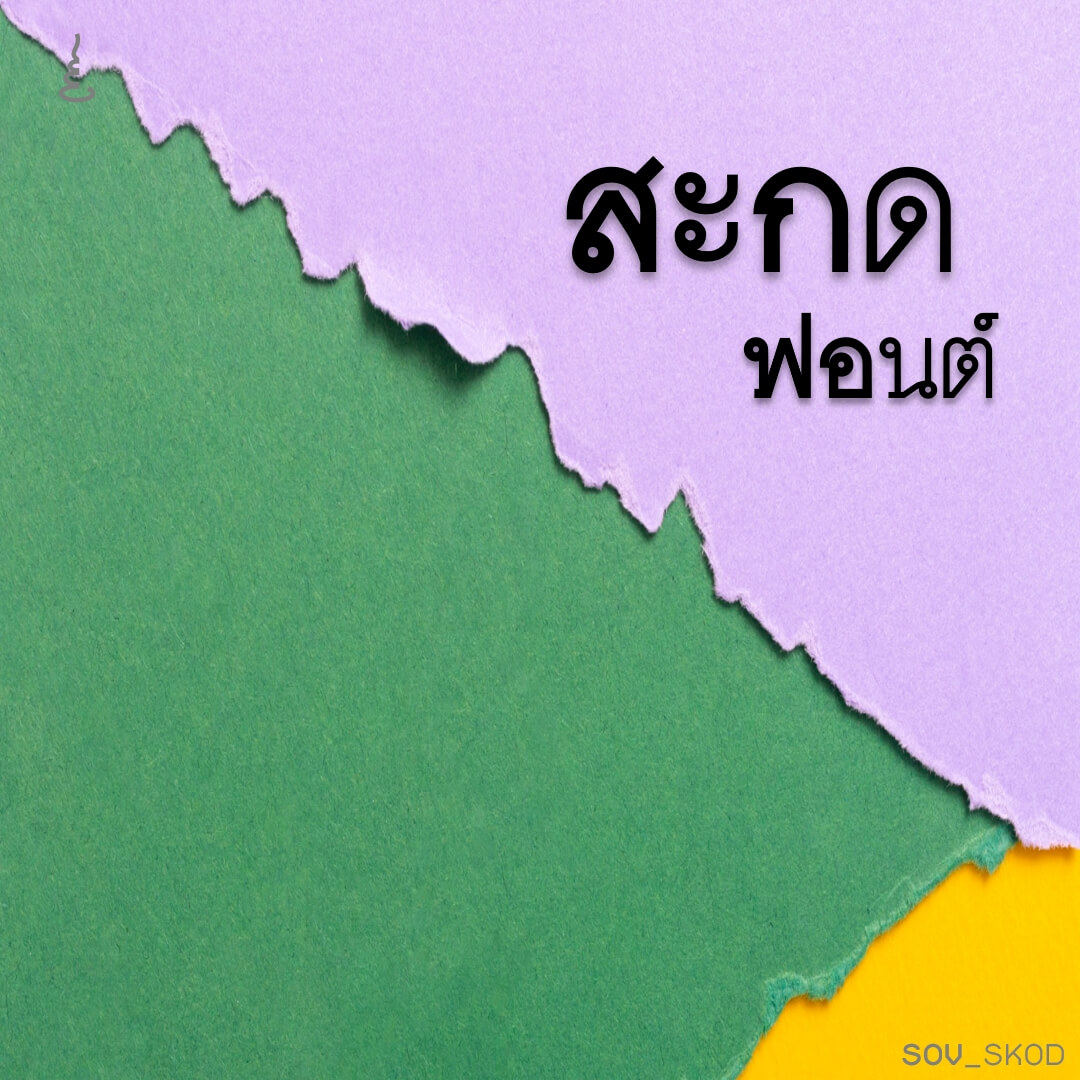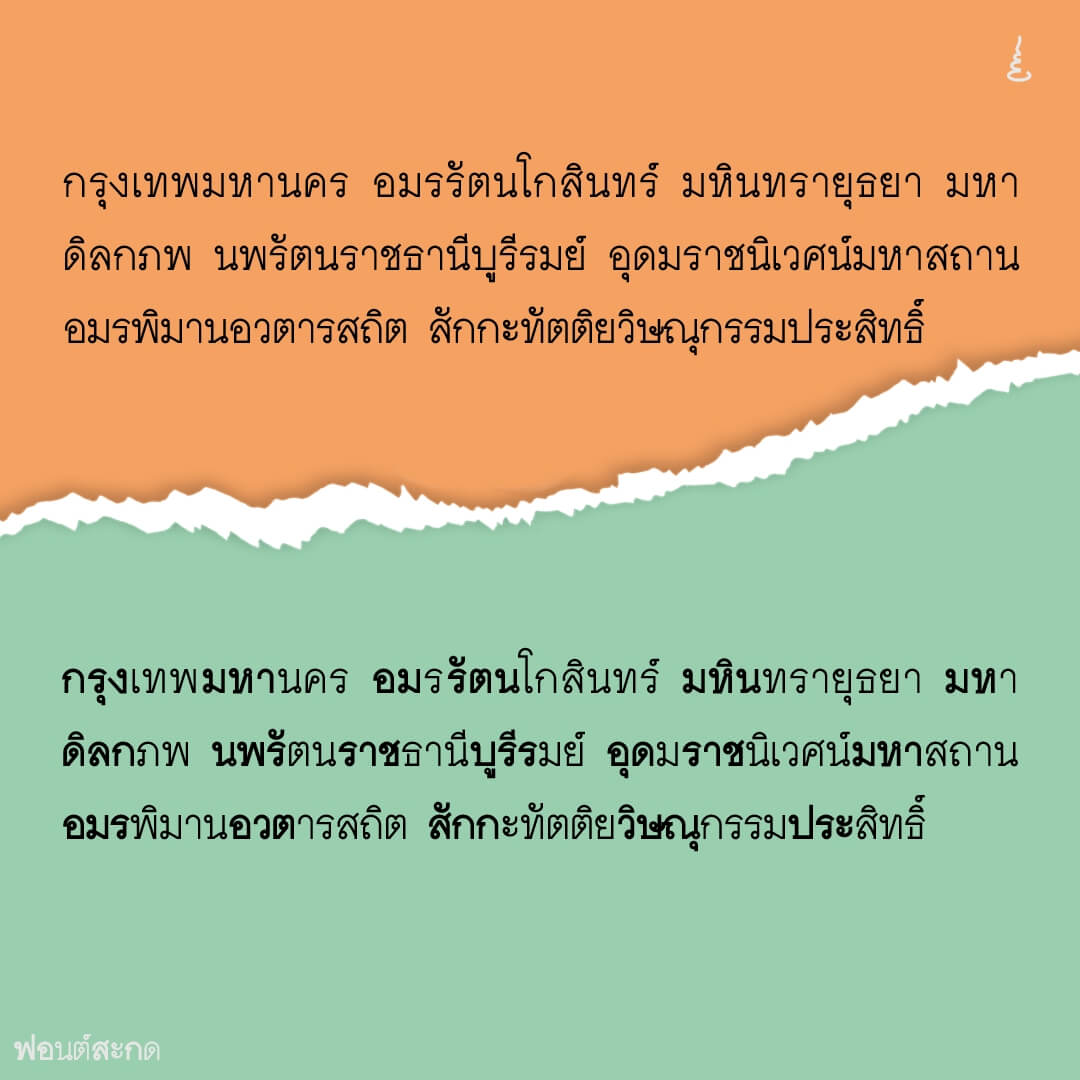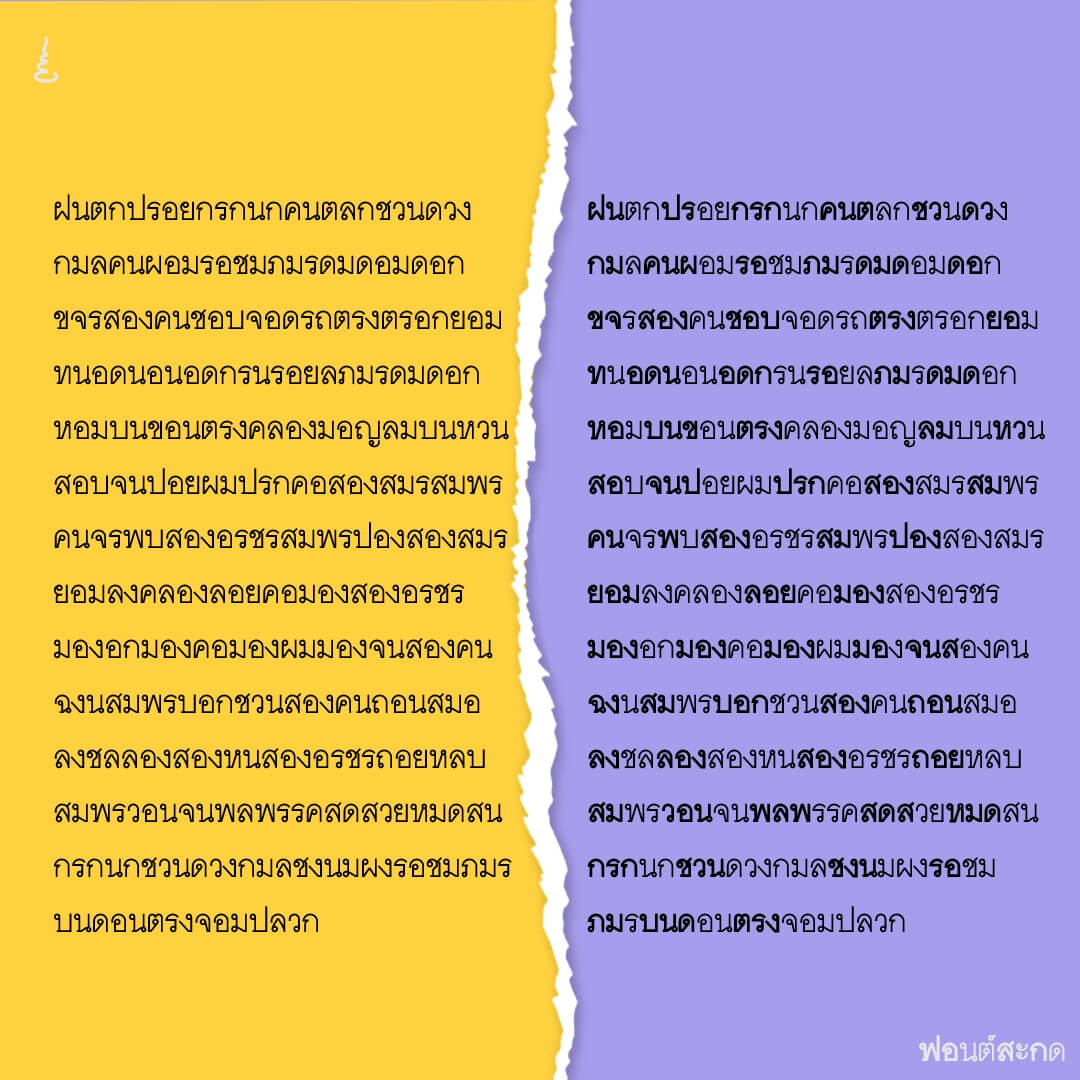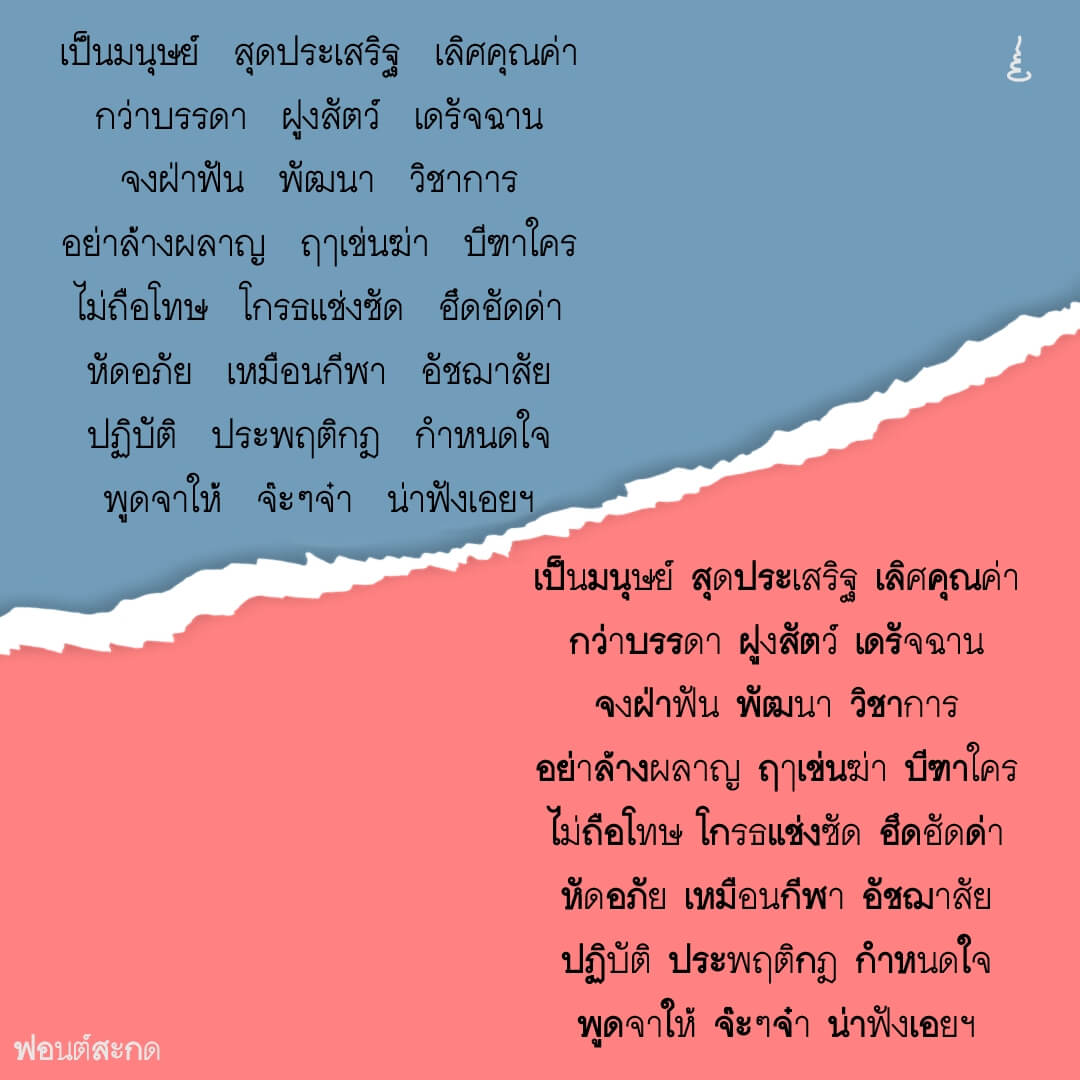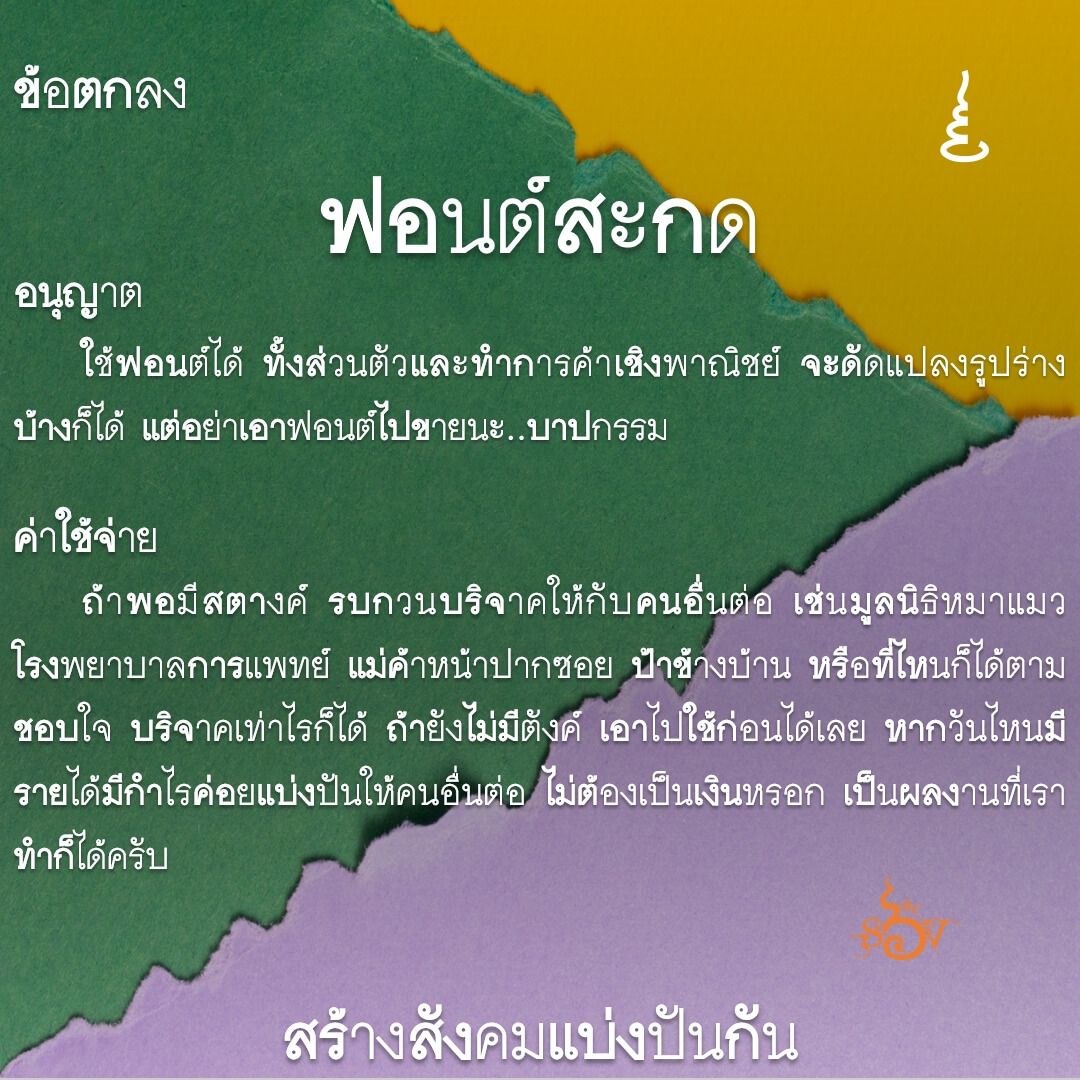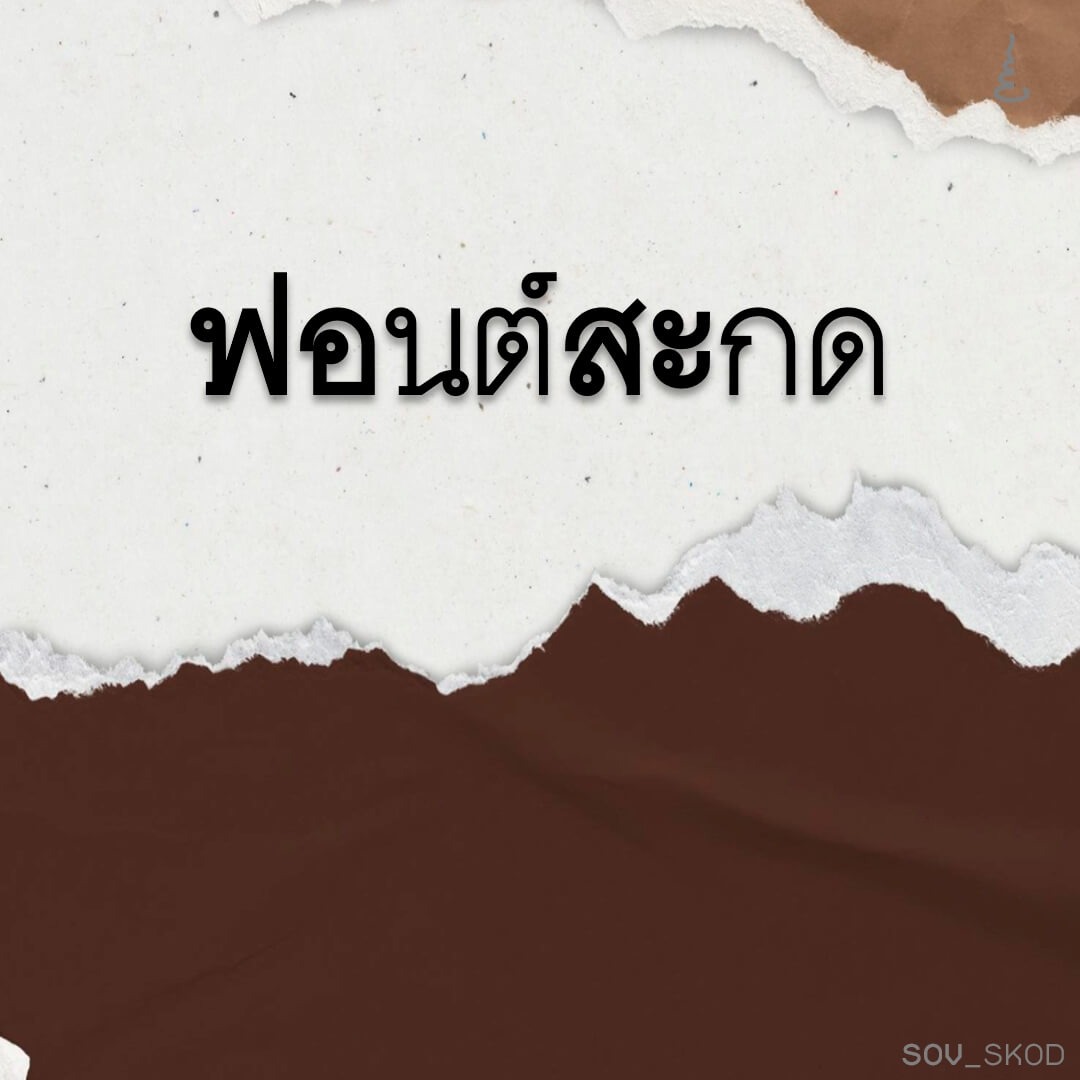
ฟอนต์สะกด แนวคิดมาจาก Bionic Reading เทคนิคทำให้อ่านเร็วขึ้น ต้นแบบใช้ application ช่วยในการจัดการตัวอักษร แต่ฟอนต์สะกดไม่ต้องใช้ app ใดๆ ฟอนต์จัดการตัวเองได้ ว่าจะให้อักษรหนากี่ตัว
วิธีการใช้คือ ให้เคาะ space หน้าคำที่ต้องการเน้นให้อ่าน ถ้าต้องการเว้นวรรค ให้เคาะ space 2 ตัวติดกัน… ลองอ่านกันดู
สะกด (SOV_skod)